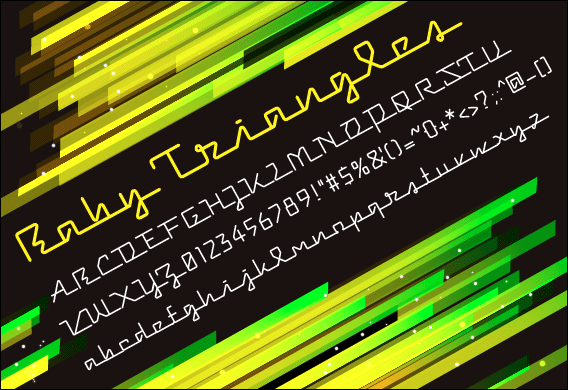
ベイビートライアングルズフォント
Baby Triangles(ベイビートライアングル) という文字のつながりが面白いフォント。三角形っぽいデザインはシャープでインパクト大。ネオンライトみたいな使い方や、タイトルロゴへ使うのも良いのではないでしょうか。音楽で言うとテクノ(テクノポップ)系に良くマッチすると思います。バキバキのテクノというよりは、ちょっと可愛らしいイメージですかね。作ったきっかけはパフュームのlove the worldのタイトルを見た時に、こういうつながり系のタイトルロゴに向くようなフォントができないかなと。そんな感じなので直角二等辺三角形を基調にしながらも、小文字のrやsなどのクルッとした感じがカワイイ感じを醸し出していると思います。��